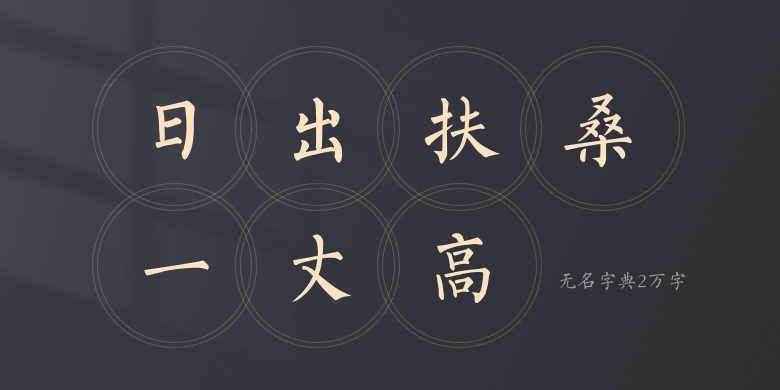
无名字典2万字
无名字典2万字,这款字体结构工整、笔画清晰,兼顾美观与易读性,适用于标题、正文、海报、包装、LOGO 等多种场景。字形优雅稳定,风格百搭耐看,适配日常排版与创意设计,让文字呈现更舒适、更具质感。无名字典2万字一笔一画,皆是细节,以均衡的比例、流畅的线条打造舒适视觉体验,字形端正大气,风格简约现代。无论是商业设计、品牌宣传还是日常排版,都能轻松驾驭,让文字更有格调与力量。无名字典2万字字体下载。